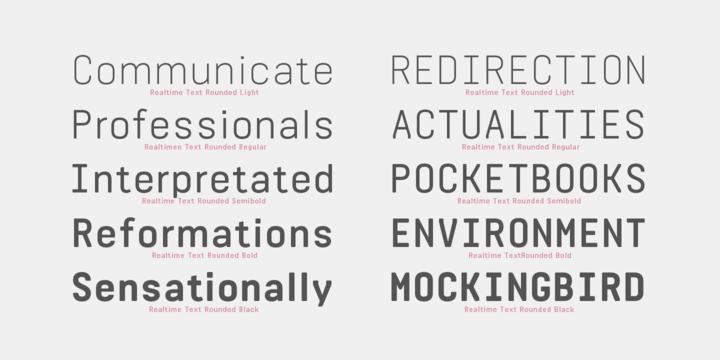
Welche Schrift ist das? Eventuell eine Ähnliche ?
wer kennt folgende Schrift? Oder kennt jemand eine ähnliche kostenfreie "moderne" Monospace Schrift?
Hintergrund ist folgender: Dem Kunden ist die vorgeschlagene Monospace Schrift "Source Code Pro" zu altbacken, sprich zu stark Schreibmaschinenschrift / "Courier". Die Absicht ist nun die Grundzüge einer Monospace Schrift beibzubehalten, aber nicht so enggestellt und weniger ausgeprägen Monspace Stil zu bekommen. Hierbei bin ich auf die Schrift im Anhang gekommen. Es muss nicht zwingend die sein, aber eine ähnliche mit mehreren Schriftschnitten und kostenfrei.
Bei der Schrift handelt es sich um T-Star Mono Round. Sie ist in drei Schnitten verfügbar. Zwar nicht kostenlos, jedoch relativ günstig.